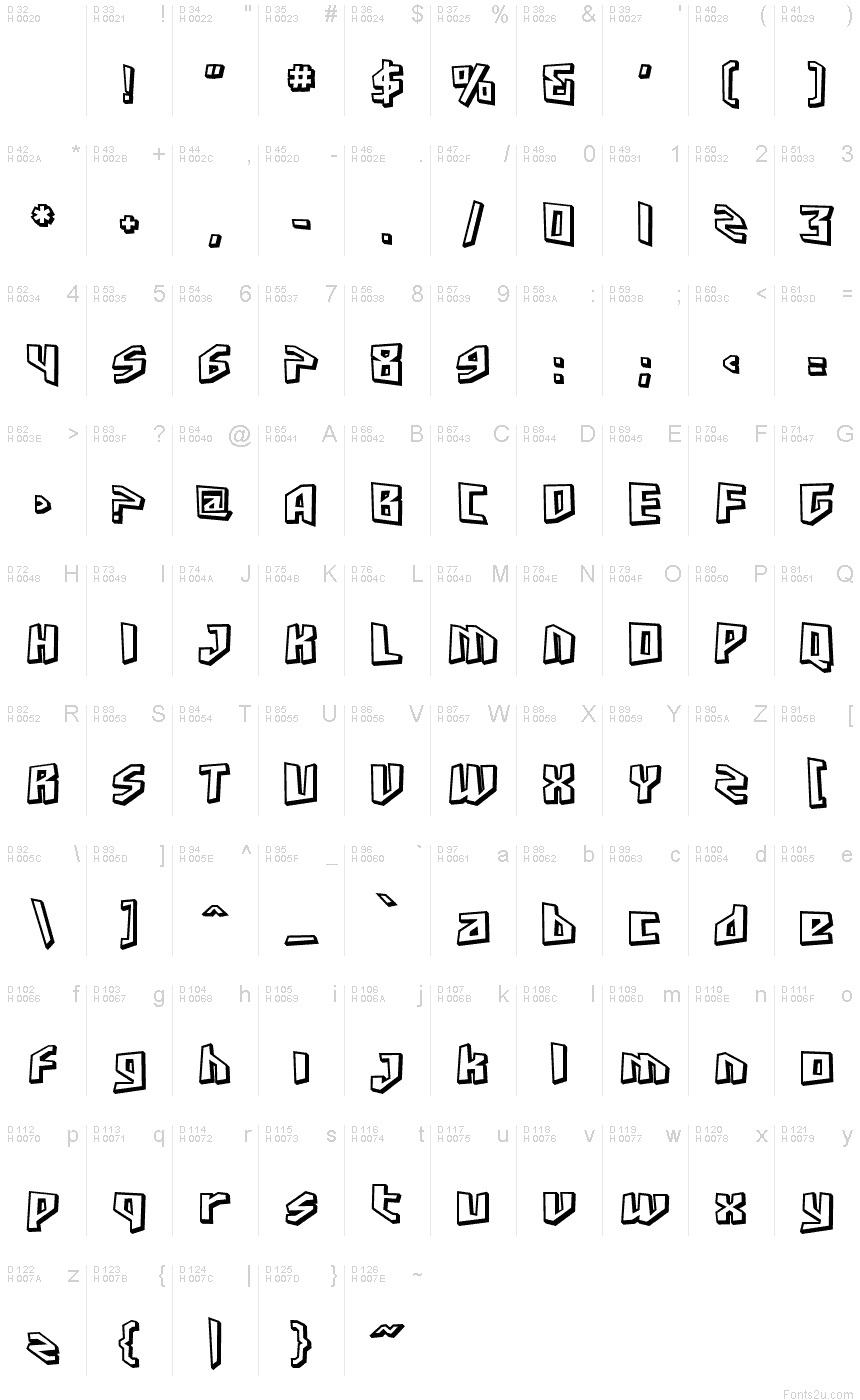
SF Junk Culture Shaded od ShyFoundry to bezpłatny, komiksowy font 3D, który oddaje luźną, ręcznie wycinaną energię ulicznych plakatów i szkolnych notatek, zamkniętą w masywnej bryle. Litery nachylają się i wpadają na siebie pod nieregularnymi kątami, mając grube obrysy i efekt cieniowanego bloku, co nadaje krojowi zabawnego i nieco surowego charakteru, zamiast gładkiego, cyfrowego wykończenia.
Pasuje idealnie do zinów, ulotek skejtowych czy muzycznych, okładek mixtape’ów, plansz tytułowych i krzykliwych opakowań, gdzie nietypowa perspektywa staje się częścią przekazu. Jako darmowy font sprawdza się również w krótkich nagłówkach, szkicach logo i plakatach, które potrzebują odrobiny miejskiej energii – nachylone kształty i mocne cieniowanie błyskawicznie przyciągają wzrok.
SF Junk Culture Shaded
ShyFoundry
Derek Vogelpohl